斜めでスタイリッシュなイタリックフォント13選
イタリックフォントの中でも斜めでスタイリッシュなフォントを13選まとめました。アルファベットを斜めにすることでスタイリッシュさが増します。今回ご紹介するイタリックフォントを使うことで簡単にかっこいいデザインにすることができます。
Automatic
頭がトンガった部分がチャームポイントの斜体フォント。
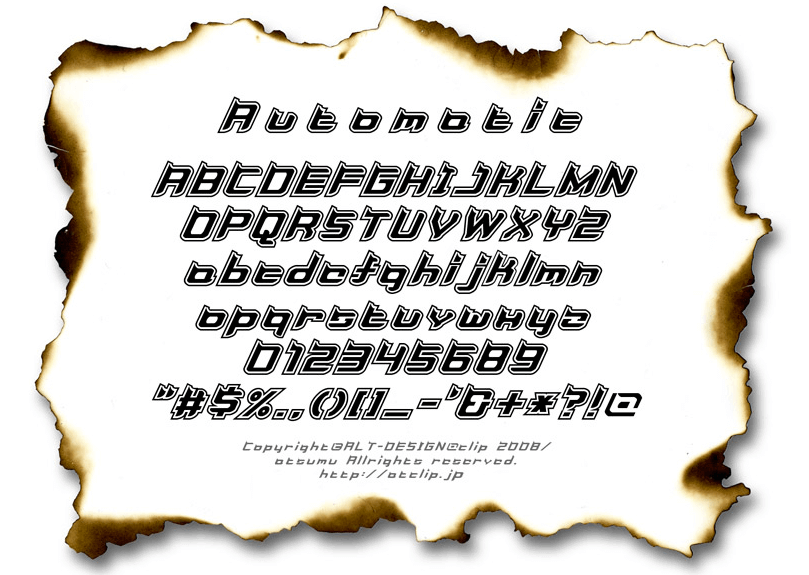
Celbo Family
細長の欧文イタリックフォント。
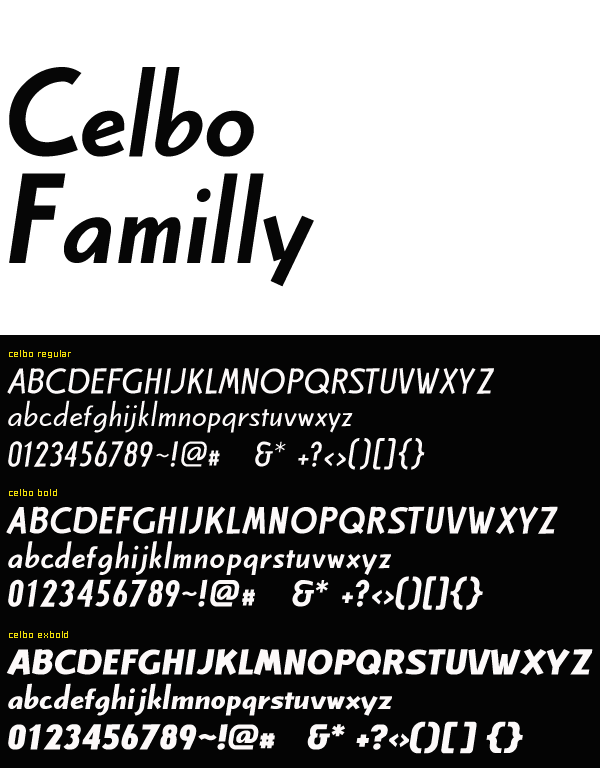
Childish-AL, KT, HR
デジタルっぽい斜めに傾いたフォント。Nintendo DS新発売の際、CMで使用されたフォントだそうです。
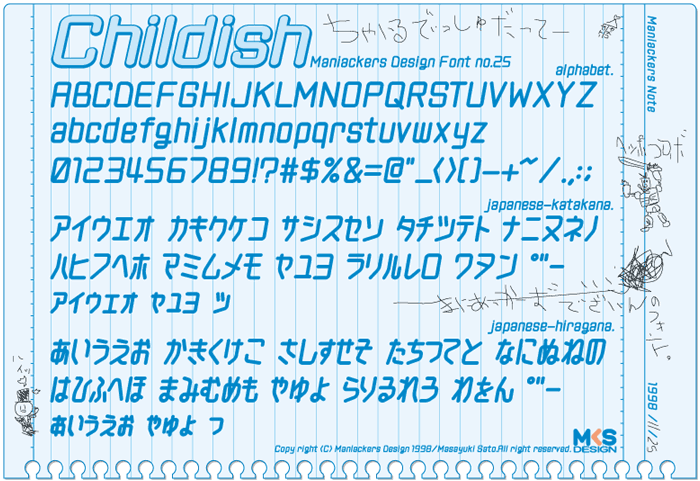
City Family
文字の最後がひげのように伸びているフォント。
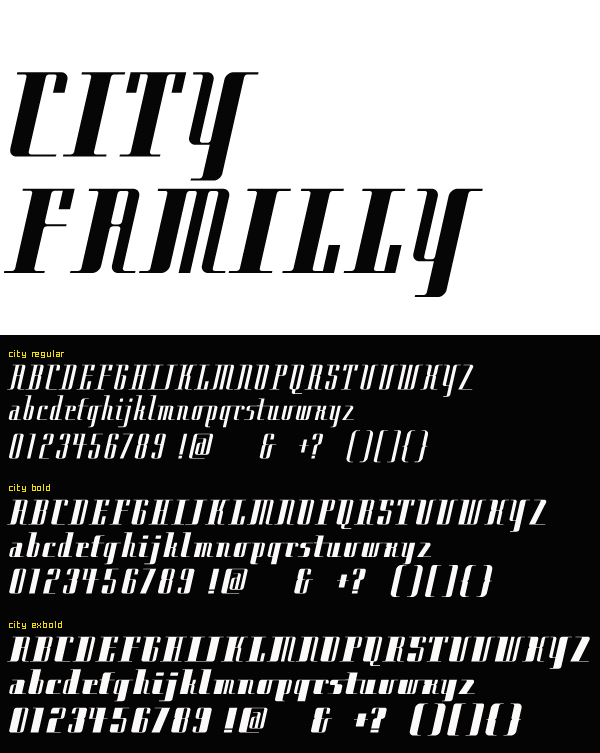
Comons Family
文字の最初が流れるようなデザインをしたフォント。
Contact Family
ステンシルタイプの斜体フォント。
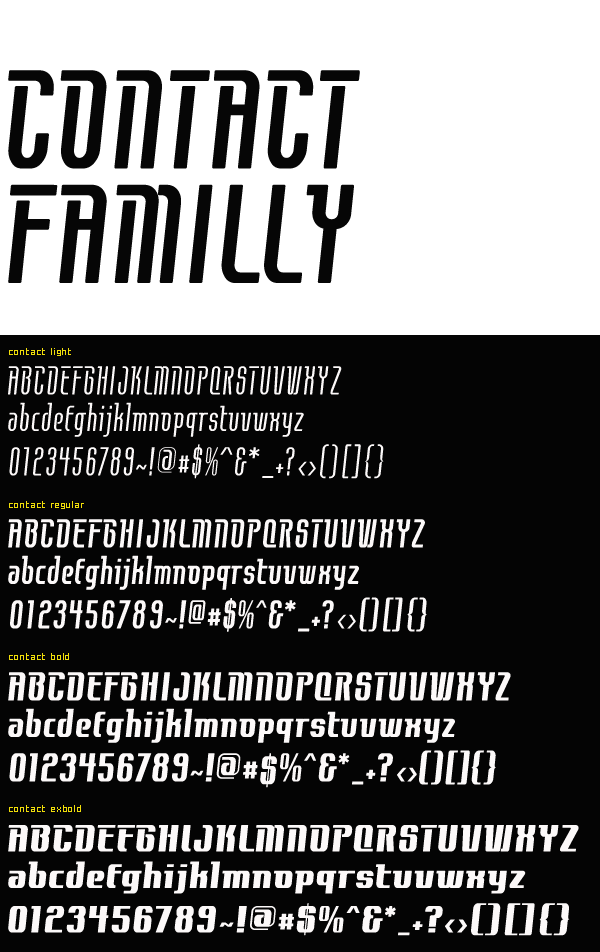
Comoy Regular
読みやすい欧文イタリックフォント。レギュラーウェイトのみです。
Cream Family
文字が膨らんだ欧文フォント。3種類のウェイトが用意されています。
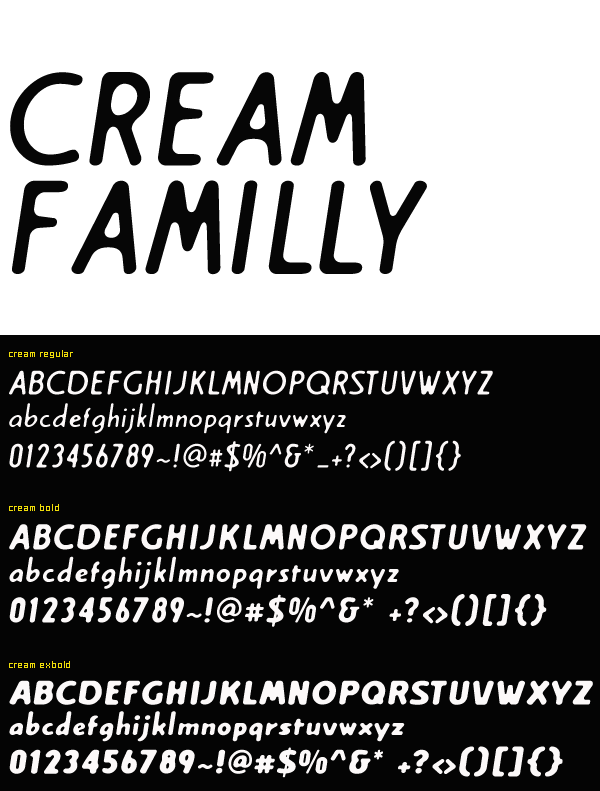
Cupola Roman
文字のところどころにクルットした遊び心がデザインされたフォント。
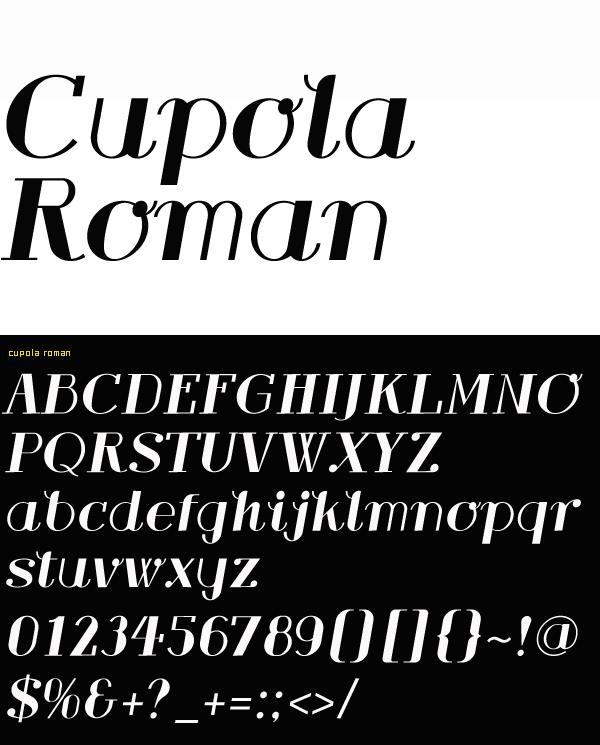
Korrekt Oblique
文字の各パーツを単純化した、シンプルでパワフルなフォント。
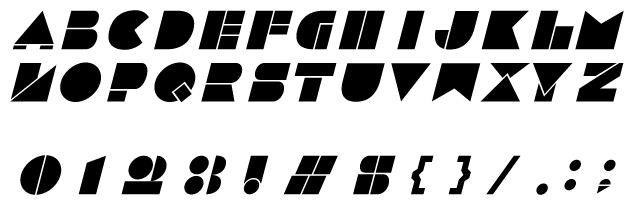
Love Rocket NEO
横幅が広がった斜体フォント。
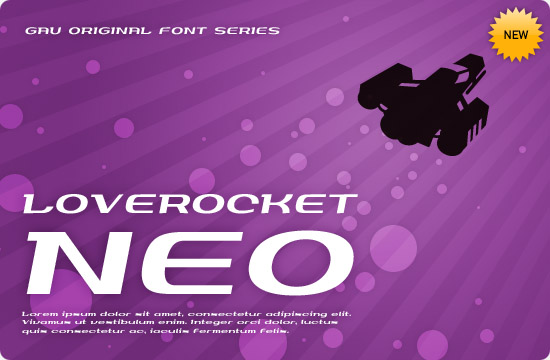
shuttle
カクカクっとした直線的なインタリックフォント。
ゆたまる
大きいサイズがおすすめの欧文(TrueType)フォント。